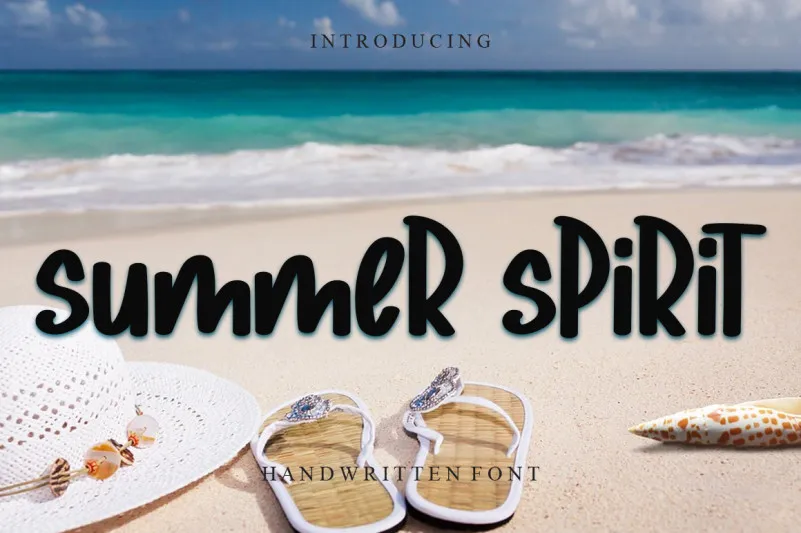
Summer Spirit Font – Fonte Grátis
Summer Spirit Font
A Summer Spirit Font é uma aquarela de letra cursiva única que promete tornar suas ideias criativas ainda mais autênticas e artísticas. Aproveite sua função como fonte tanto para Instagram quanto como um script decorativo para projetos DIY, garantindo o resultado desejado em qualquer trabalho de arte digital ou impressão. Ideal para aqueles que buscam uma letra elegante e divertida ao mesmo tempo, essa font pode transformar seus textos em verdadeiros trabalhos de arte, encantando não apenas com sua aparição delicada e colorida, mas também com seu uso versátil. Seja você um designer ou simplesmente alguém que deseja dar mais vida a suas criações digitais, Summer Spirit Font certamente se adequará perfeitamente ao seu estilo único.